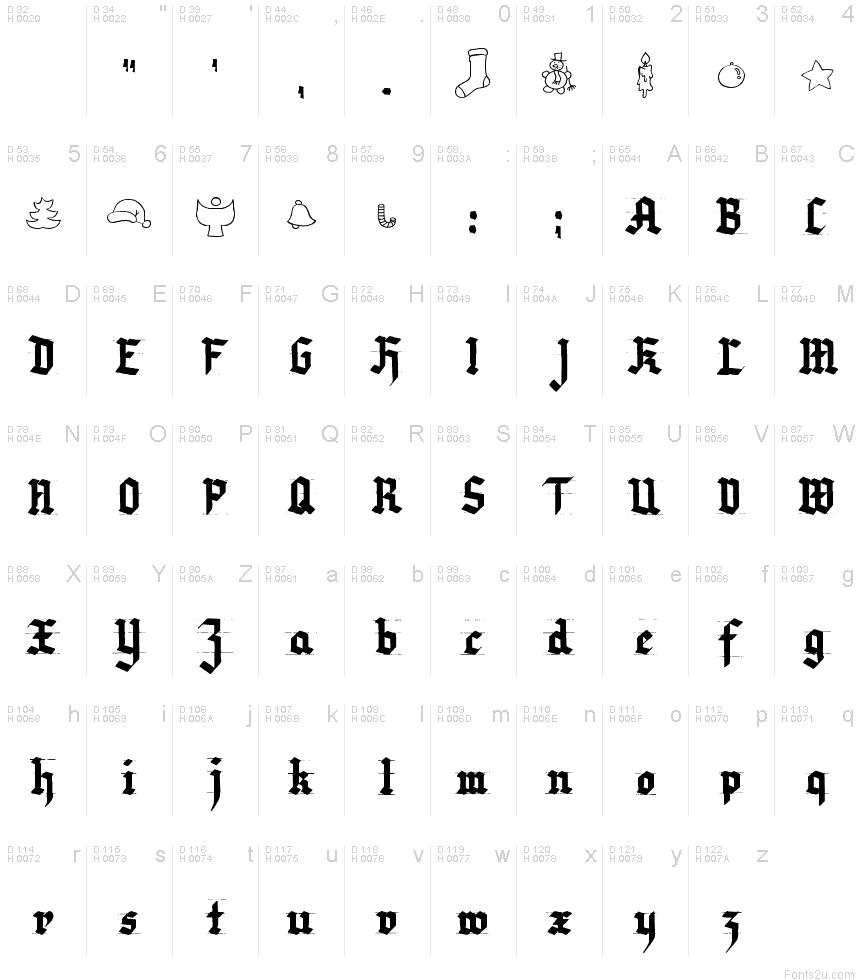
Very Christmess autorstwa Jakoba Fischera to darmowy font typu blackletter o ostrym, świątecznym, gotyckim klimacie. Litery opierają się na łamanych kątach, przyciętych rogach i spiczastych zakończeniach, co nadaje krojowi dramaturgii znanej ze starych śpiewników kolędowych. Jednocześnie lekko surowe krawędzie sprawiają, że całość nie sprawia wrażenia sztywnej czy muzealnej.
Sprawdza się w nagłówkach plakatów, opakowaniach sezonowych, ulotkach wydarzeń, okładkach albumów czy menu pubów, gdzie darmowy font może wnieść klimat dawnych ceremonii bez nadmiernego przepychu. Dzięki kompaktowym i wyrazistym formom, font pasuje również do krótkich tytułów i inicjałów, zwłaszcza gdy zależy Ci na szybkim i czytelnym zimowo-średniowiecznym akcencie.